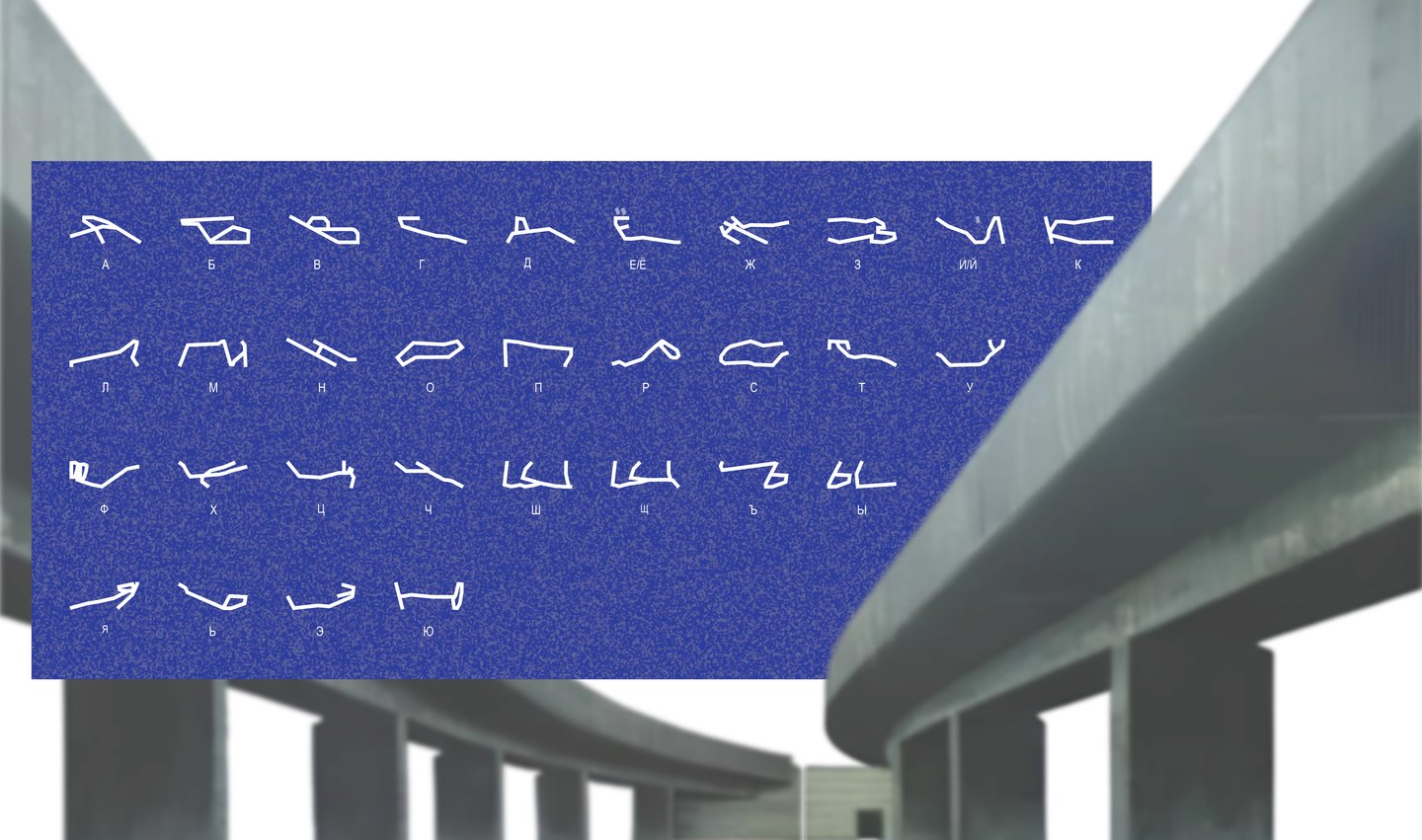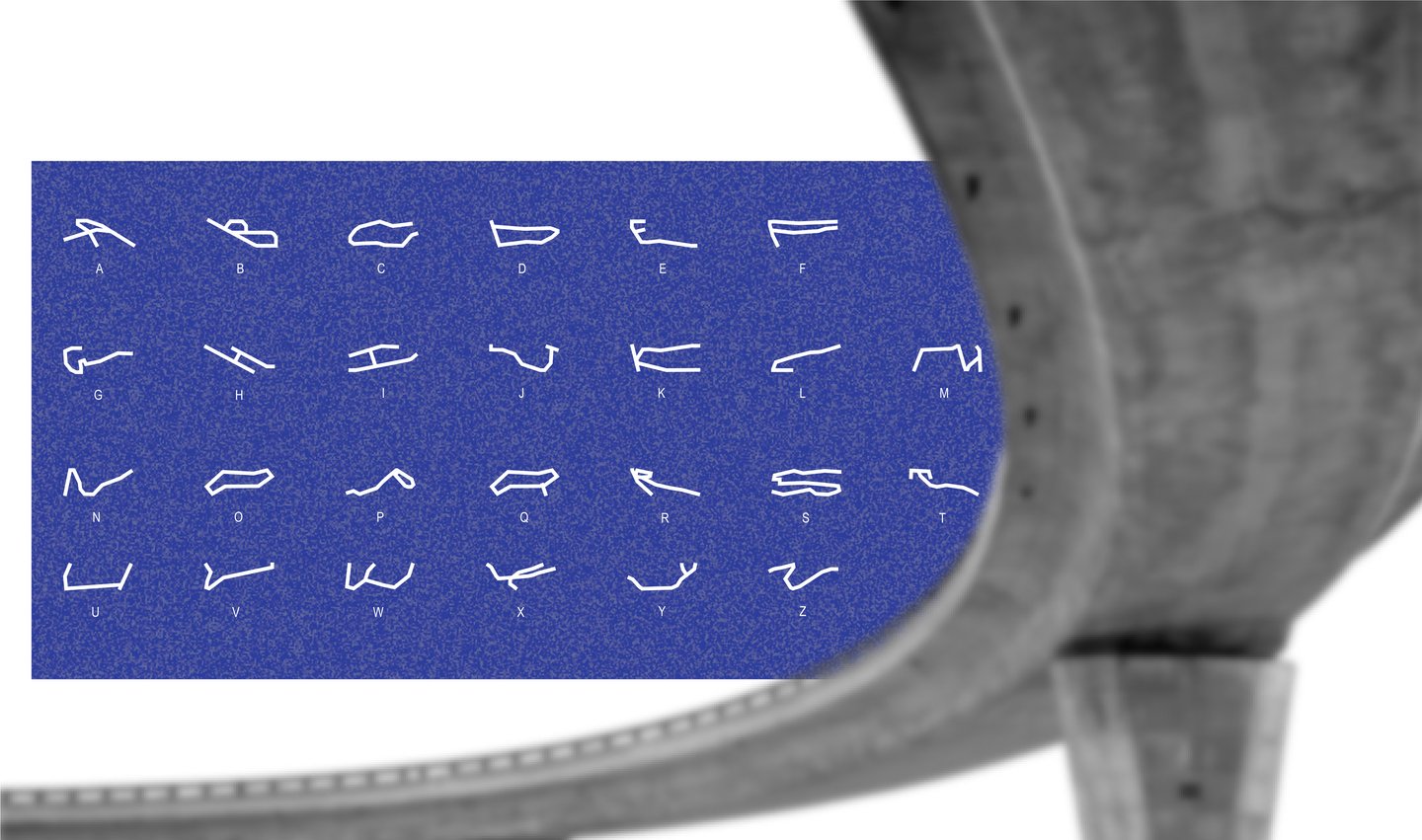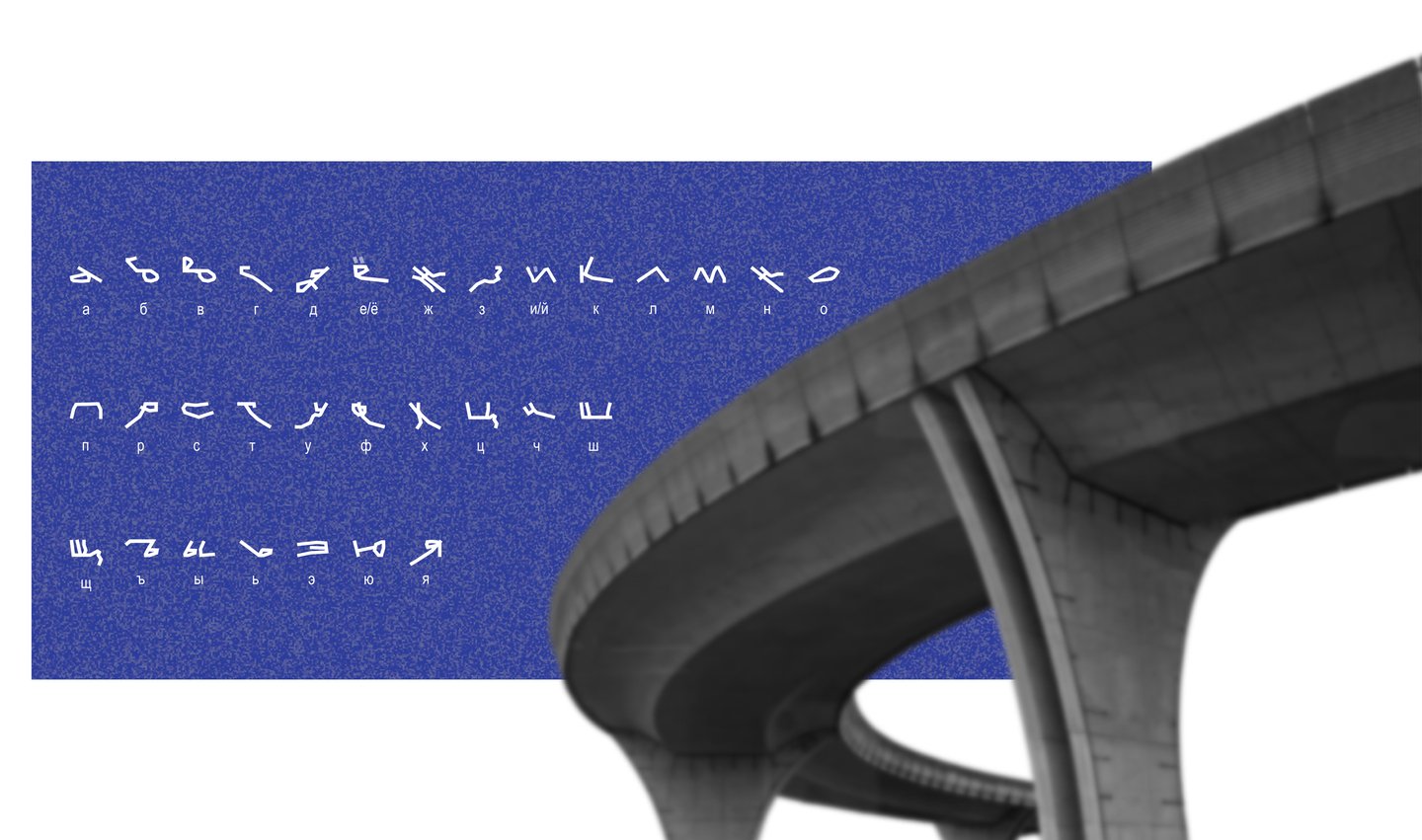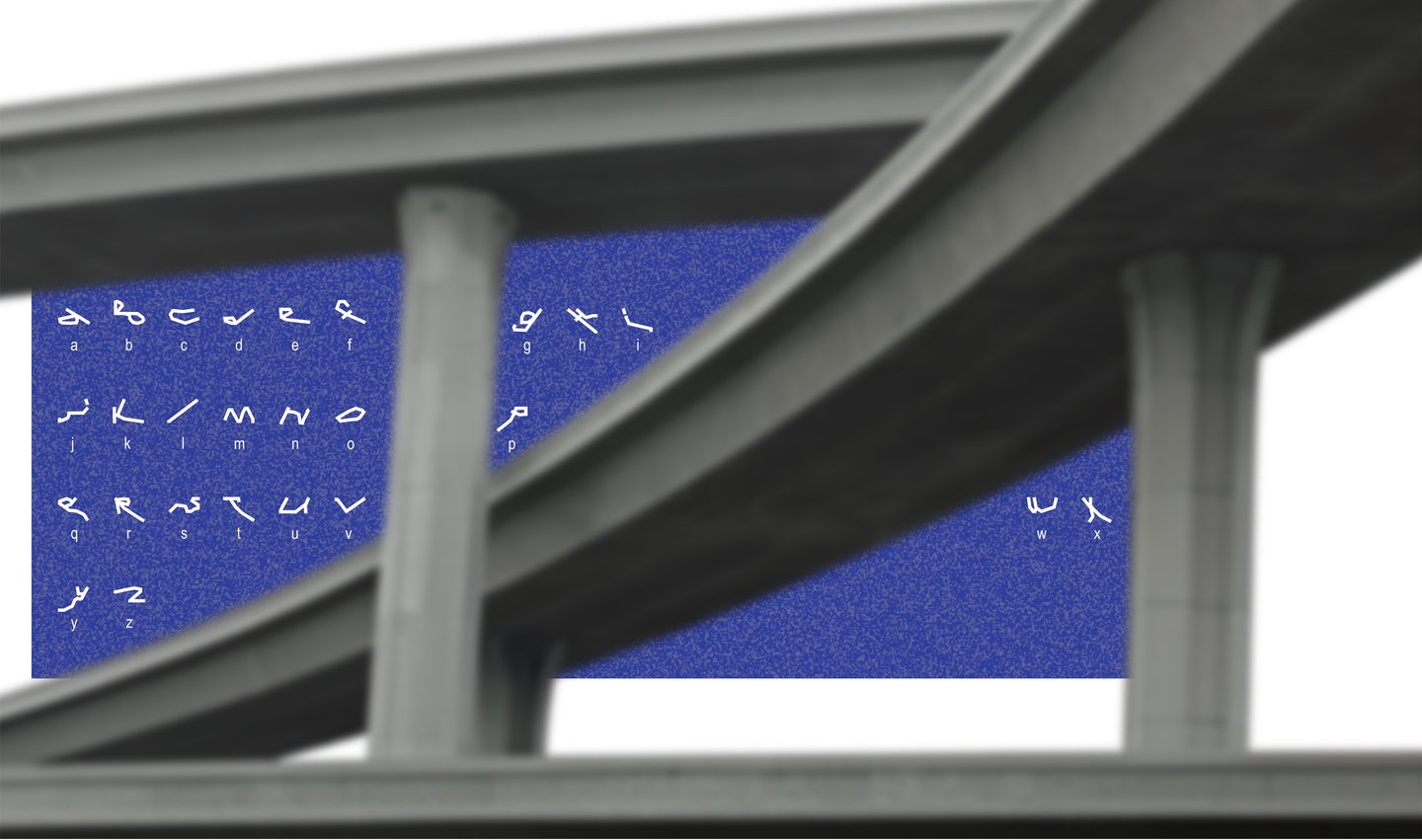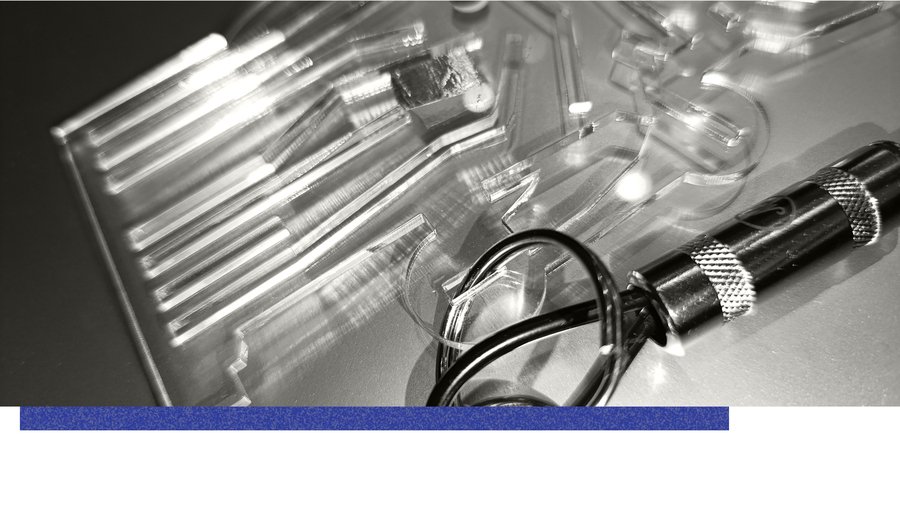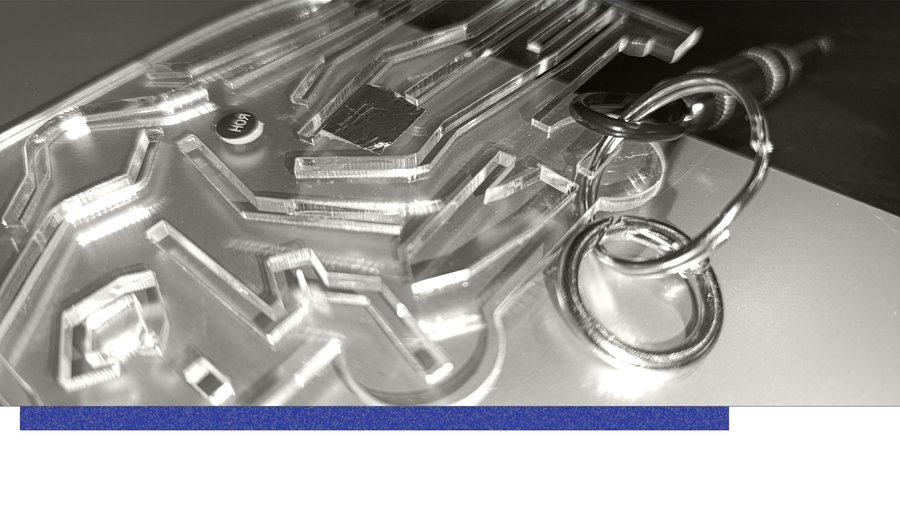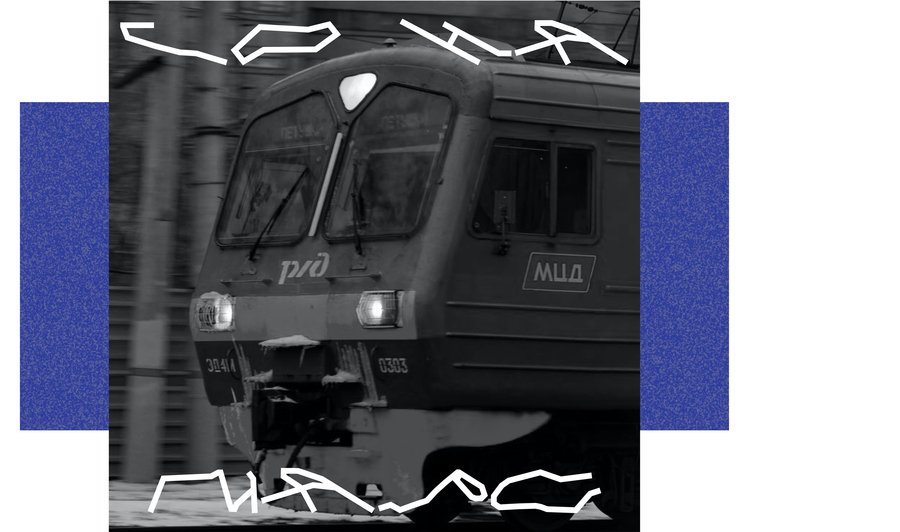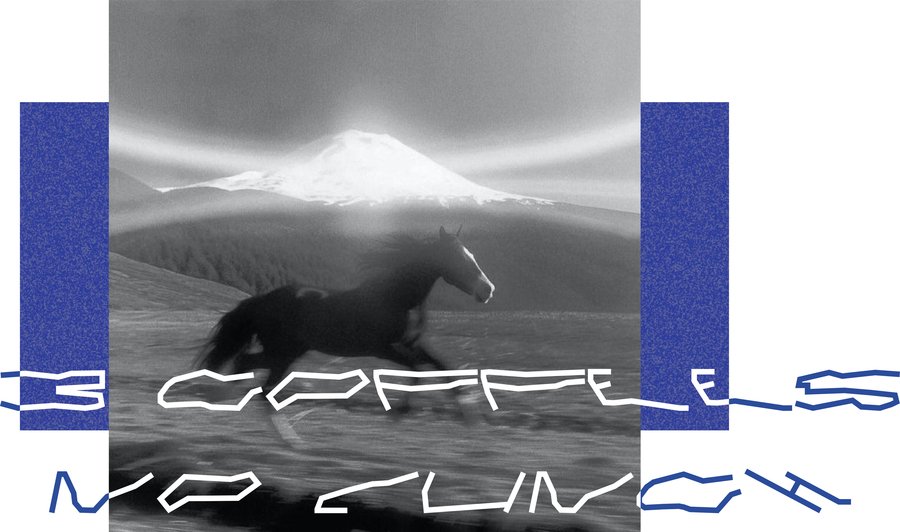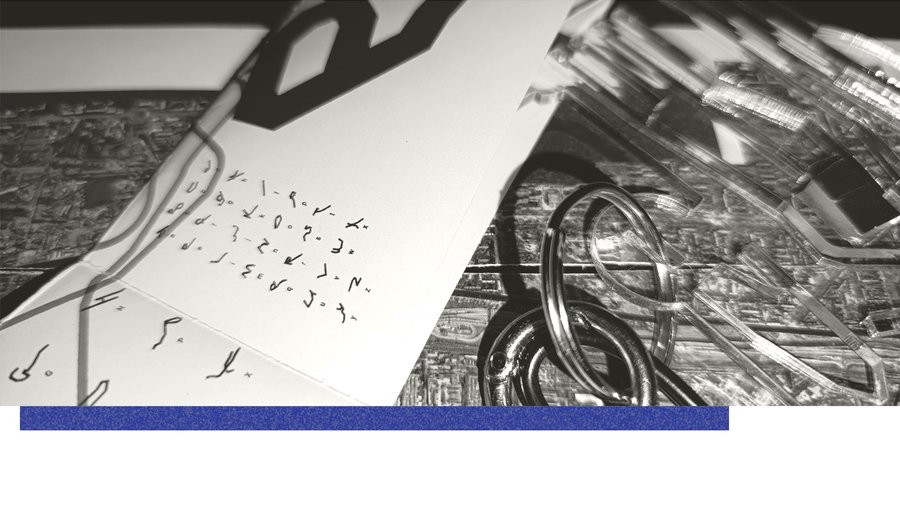
TRNS // модульный шрифт
Результат «полевого исследования», формообразование не из поездов и путей (как задумывалось ранее), а из нервного ожидания на остановке, случайность.
TRNS — модульный шрифт, вдохновленный переходом, транспортом, трейнспоттингом, бегом по лезвию и по городу, внезапным наблюдением за поломанной рабицей и «нервяком».
Каждая буква сложена из собственного изгиба заградительной сетки, создавая новый беспорядочный путь.
Кириллица: прописные и строчные
Латиница: прописные и строчные
Использование шрифта. Слева: «го на марс», справа: «3 coffees no lunch»
Дополнительные символы
Шрифтовая линейка — физический носитель, выполненный из оргстекла. Миниатюрный, выполненный в форме первого вагона электрички «Ласточки» он — отправная точка движения.
Зин о шрифте TRNS — в первую очередь переживание, а не удачный физический носитель. Намеренное избегание профессиональное печати позволило добиться ощущения «случайного флаера (или забытого билета) в кармане», усилить нарратив «сделано/замечено на бегу».
Первый «том» рассказывает про эмоциональную составляющую, второй — про итог работы. Зин — плохая карта.
«Том-1»: переживание
«Том-2»: результат